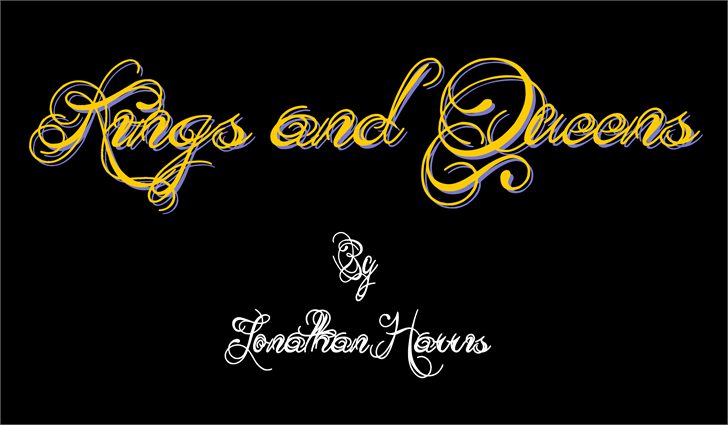
A Kings and Queens font é uma escolha perfeita para os designers que buscam adicionar uma pitada única ao seu trabalho gráfico. Essa elegante fonte traz à tona uma variedade de estilos, adequados tanto para criações personalizadas quanto para uso comercial, desde letras finas e românticas até textos mais robustos e vibrantes. O designer Hamilton criou um conjunto de letras que captura a essência do luxo e da elegância. A Kings and Queens font tem uma aparência suave mas resistente, tornando-a ideal para aplicativos variados como editoriais, publicações online e até mesmo materiais de marketing, garantindo uma experiência visual agradável e profissional em qualquer projeto. Quer explorar mais esse charmoso conjunto de letras? Pode ser utilizado apenas com uso pessoal sem problemas. Para uso comercial, basta seguir os termos de uso da marca fornecidos no site oficial do criador ou entrar em contato diretamente para obter orientação e licencas adequadas. Estamos orgulhosos de oferecer a Kings and Queens font, uma escolha gráfica que não só impressiona pelo seu design elegante, mas também por sua versatilidade. Por favor, consulte a documentação oficial para maiores detalhes e instruções sobre como utilizar esta incrível font.